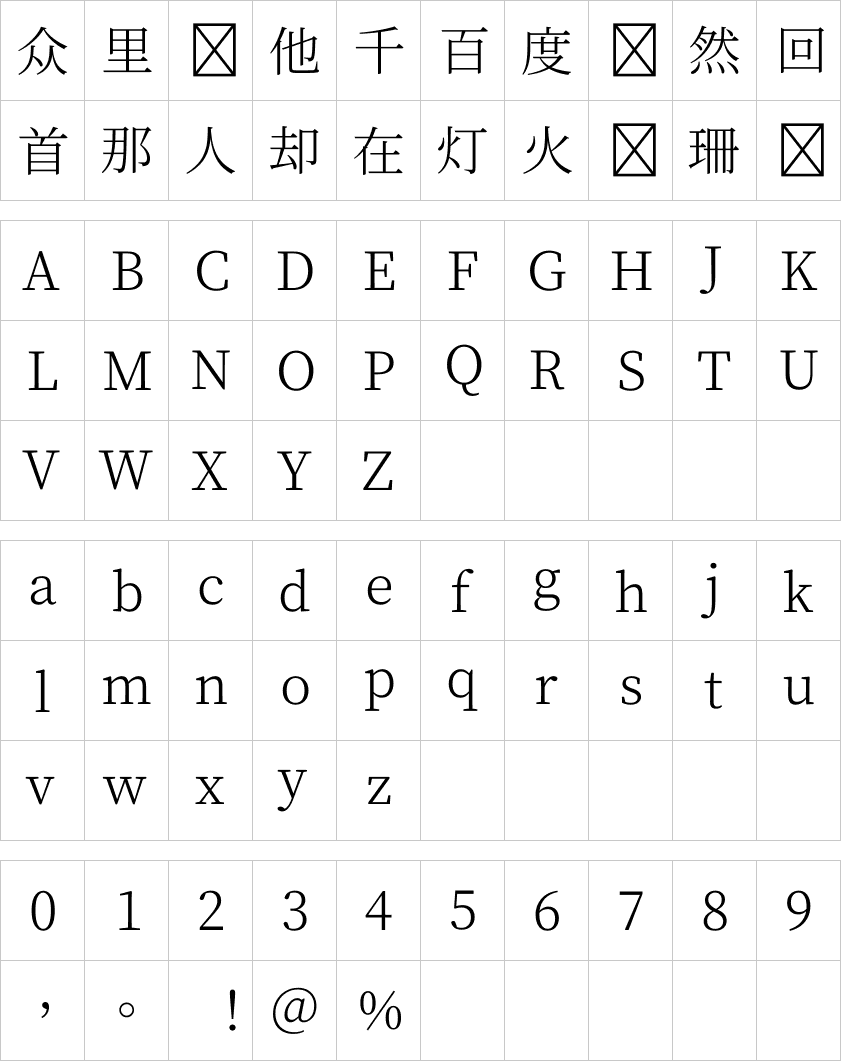
源样明体-Light
源样明体由台湾字型社团「字嗨」管理员 But Ko基于“思源宋体的”修改衍生而来,字体改造虽以计算机程序自动进行,但在一些细节调整后可以明显感受出不同效果,源样明体采用思源宋体韩文版本的字符,配合繁体中文习惯的置中标点符号,可说是兼具排版及传统印刷体风格的繁体中文字体
改造自思源宋体,传统印刷体风格且易用的繁体中文字型。